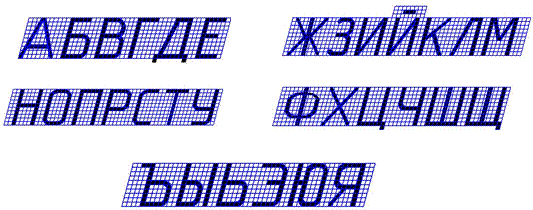
Шрифты чертежные
Масштабы изображений и их обозначение на чертежах устанавливает стандарт [8].
Масштабом называется отношение линейных размеров изображения предмета на чертеже к истинным линейным размерам предмета.
В зависимости от сложности изображаемого предмета, его изображения на чертежах могут выполняться как в натуральную величину, так и с уменьшением или с увеличением (табл. 2).
Таблица 2
Масштаб уменьшения 1: 2 1: 2,5 1: 4 1: 5 1: 10
Масштаб увеличения 2: 1 2,5: 1 4: 1 5: 1 10: 1
Начертания, толщины и основные назначения девяти типов линий, применяемых на чертежах, устанавливает стандарт [9]. В учебных чертежах наиболее часто используются шесть типов линий.
Сплошная толстая основная линия. Толщина s ≈ 0,5 … 1,4 мм (на учебных чертежах рекомендуется s ≈ 0,8 … 1 мм). Назначение: изображение линий видимого контура, линий контура сечений (вынесенного и входящего в состав разреза), внутренняя рамка чертежа и др.
Сплошная тонкая линия. Толщина от s/3 до s/2. Назначение: изображение линий контура наложенного сечения, линий размерных и выносных, линий штриховки, линий – выносок.
Штрихпунктирная тонкая линия. Толщина от s/3 до s/2. Назначение: изображение линий осевых и центровых, линий сечений, являющихся осями симметрии для наложенных или вынесенных сечений.
Штриховая линия. Толщина линии от s/3 до s/2. Назначение: изображение линий невидимого контура.
Сплошная волнистая линия. Толщина линии от s/3 до s/2. Назначение: изображение линий обрыва, линий разграничения вида и разреза.
Разомкнутая линия. Толщина линии от s до 1,5s. Назначение: изображение положений секущих плоскостей простых и сложных разрезов и сечений.
Заметим, что штрихпунктирные линии, применяемые в качестве центровых линий, должны пересекаться между собой длинными штрихами. Штрихпунктирную линию, применяемую в качестве центровой линии окружности с диаметром менее 12 мм, рекомендуется заменять сплошной тонкой линией. Штрихи (также промежутки между ними) должны быть приблизительно одинаковой длины.
Чертежные шрифты для надписей, наносимых от руки на чертежи и другие технические документы, устанавливает стандарт [10].
Размер шрифта определяется высотой прописных (заглавных) букв. Установлены следующие размеры шрифта: 2,5; 3,5; 5; 7; 10; 14. Ширина буквы определяется по отношению к размеру шрифта или по отношению к толщине линии обводки d (рис. 4).
Стандарт устанавливает следующие типы шрифта:
тип А без наклона (d=h/14);
тип А с наклоном около 75˚ (d=h/14);
тип Б без наклона (d=h/10);
тип Б с наклонам около 75˚ (d=h/10).
На учебных чертежах рекомендуется использовать шрифт типа Б с наклоном (для размерных чисел и всех надписей).
Шрифты выполняются с использованием вспомогательной сетки (рис. 4). Сетку строят тонкими, едва заметными линиями остро заточенным карандашом мар-ки Т. Это позволяет выдерживать конструкцию букв и цифр.
Рис. 4
Начертание букв по сетке делают карандашом марки ТМ или М тонкими линиями от руки на глаз. Проверив правиль­ность начертания букв, обводят их карандашом, стараясь выдержать толщину обводки. Обводить буквы нужно так, чтобы линии обводки не выходили за габаритные размеры букв. Рука при обводке должна идти слева направо и сверху вниз (рис. 5).
Рис. 5
Форма и конструкция арабских цифр шрифта типа Б с наклоном приведены на рис. 6.
Рис. 6
Форма прописных букв с наклоном русского алфавита (кириллицы) представлена на рис. 7. Ширина буквы зависит не только от размера шрифта, но и от кон­струкции самой буквы.
Рис.7
Форма и конструкция строчных букв русского алфавита шрифта типа Б с наклоном приведены на рис. 8.
Рис. 8